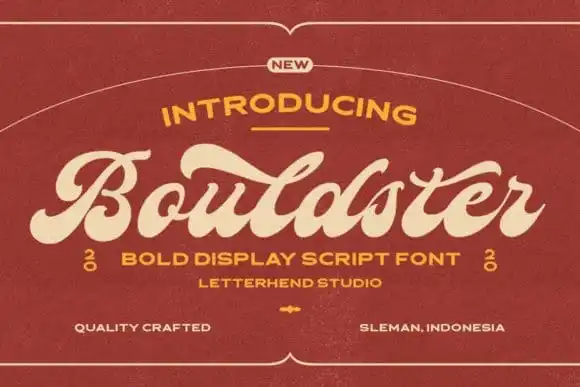
Bouldster Bold Script Font – Download Grátis
A fonte Bouldster Bold Script é uma escolha perfeita para quem quer transportar seu design para os anos 80 ou 90. Elegante e confiante, ela traz um toque moderno às antigas estéticas do passado. Especialmente projetada para headlines e logotipos, esta font é ideal para criar designs memoráveis que fazem a sua marca realmente brilhar. Ideal tanto para designers profissionais quanto para iniciantes na arte da design gráfica, Bouldster Bold Script permite que você adicione um toque nostálgico às suas criações. Suas linhas fortes e dinâmicas garantem uma aparência atraente e confiante em qualquer projeto onde você a use. Com sua simplicidade e elegância, ela é perfeita para criar elementos de marca que se destacam na tela do seu site ou até mesmo em materiais impressos. A Bouldster Bold Script vem preenchida com todo o potencial necessário para ajudar a dar um toque único ao seu design. Além disso, este produto foi criado por 99designs, uma plataforma de criação de logotipos e designs que tem sido reconhecida pela sua qualidade e variedade de fontes. Se você está procurando por uma fonte única para dar um toque especial a seus projetos, Bouldster Bold Script é uma escolha ótima.